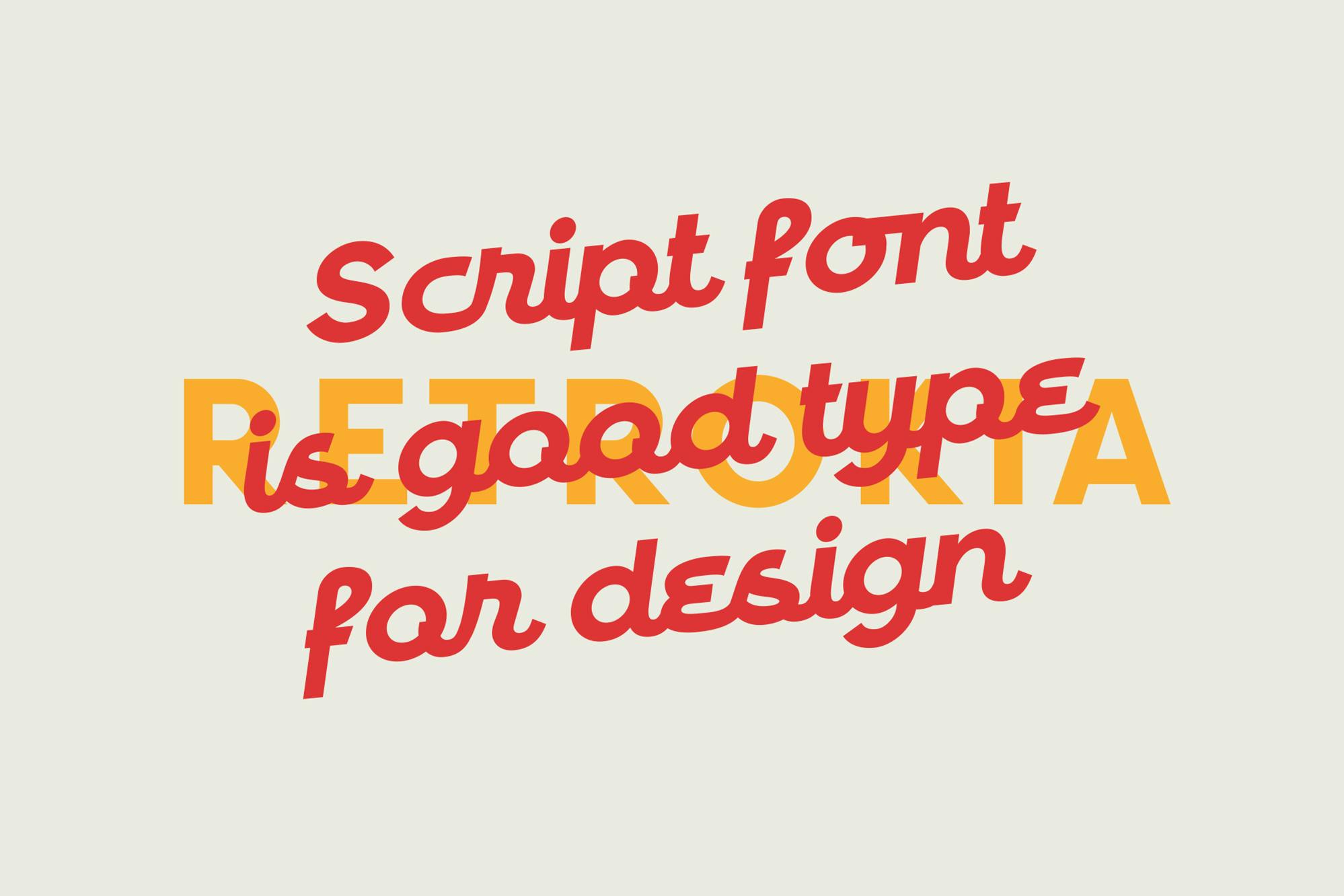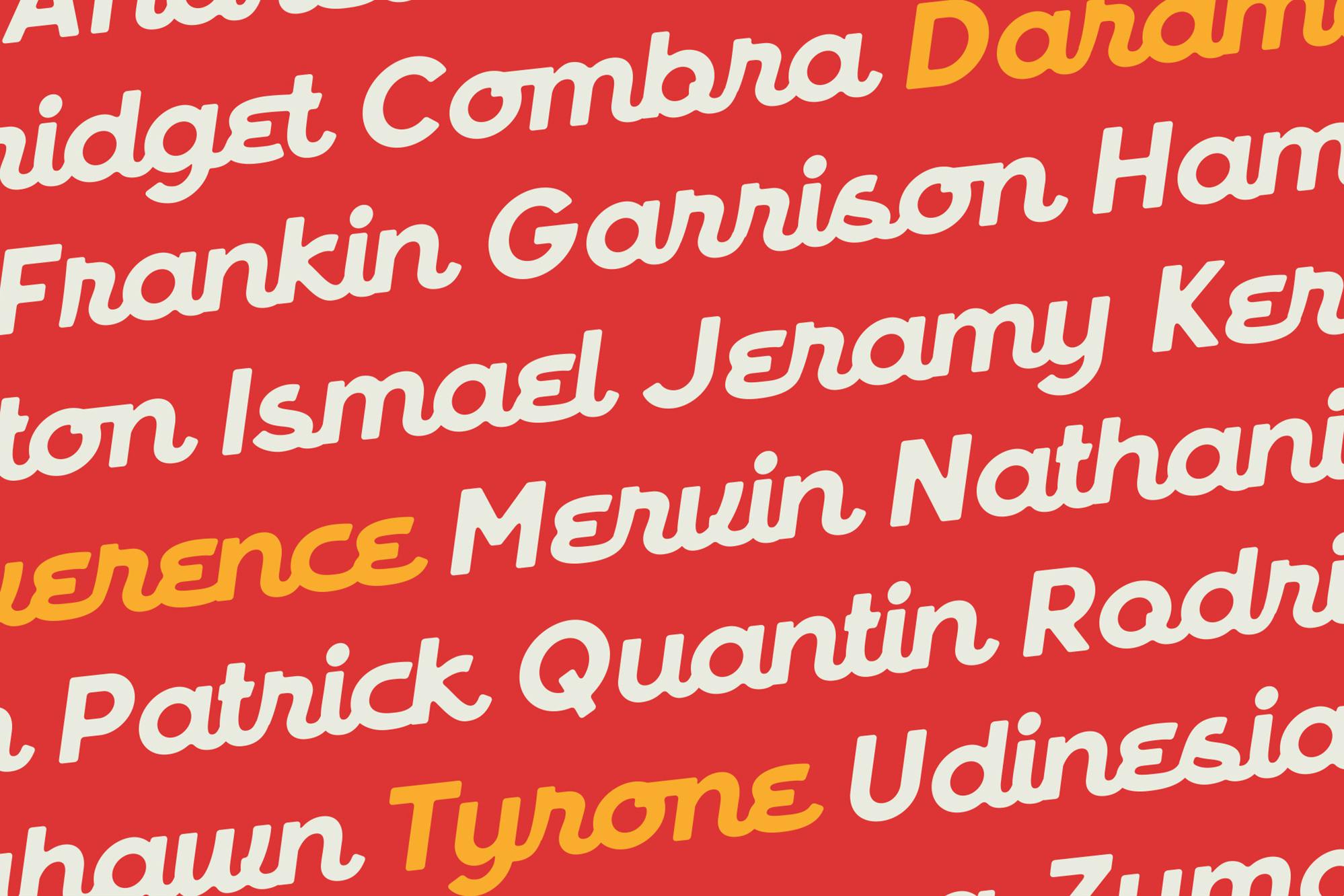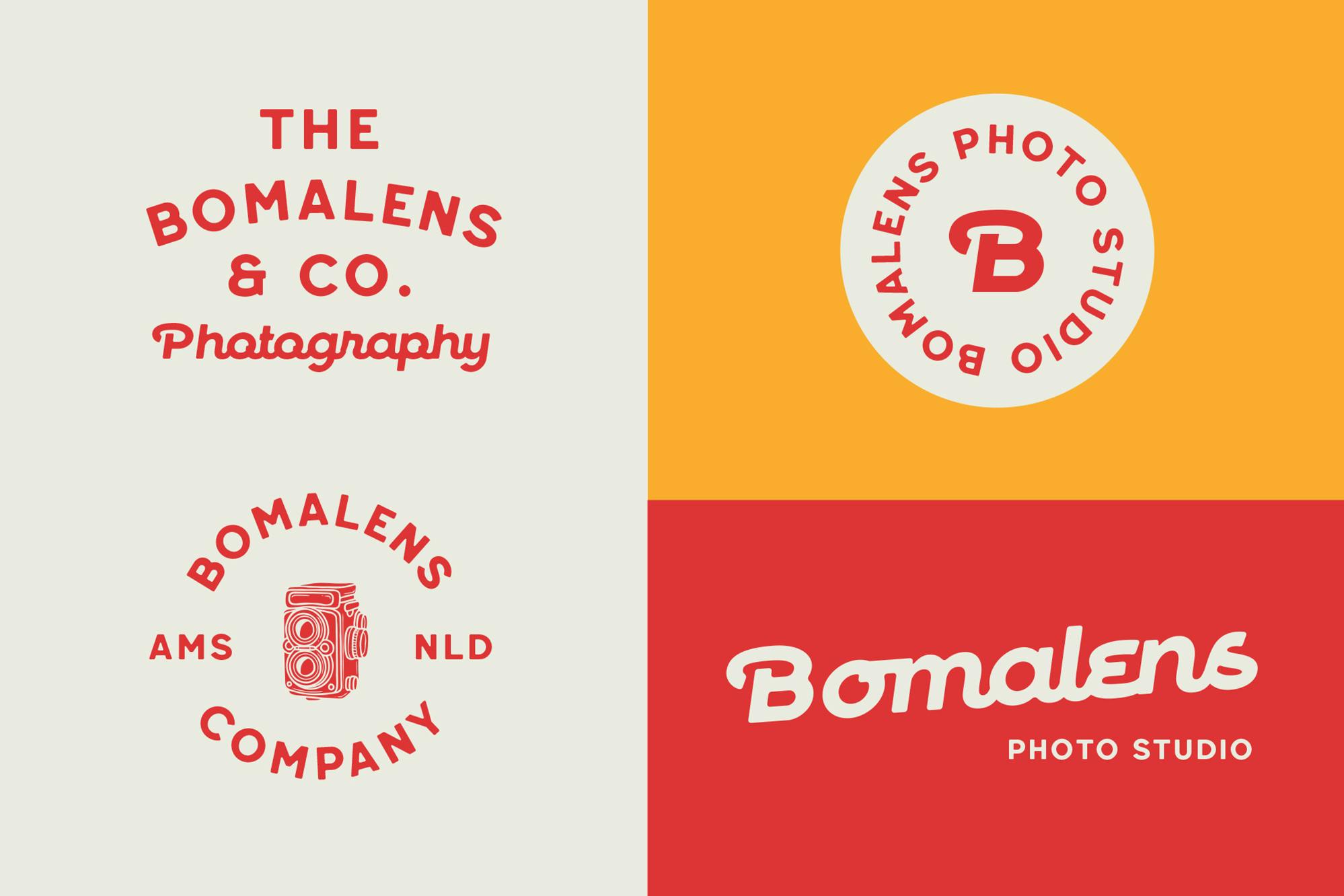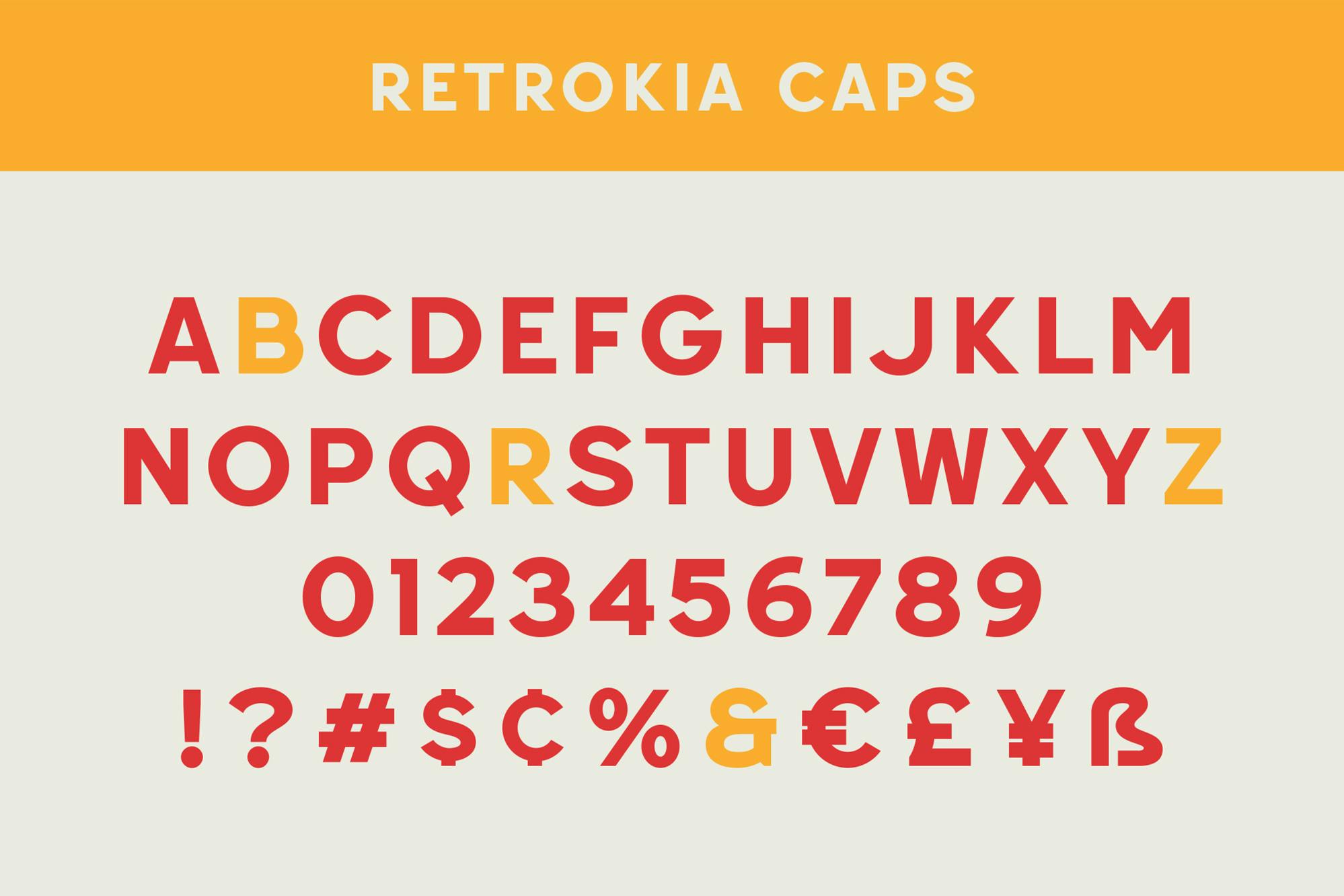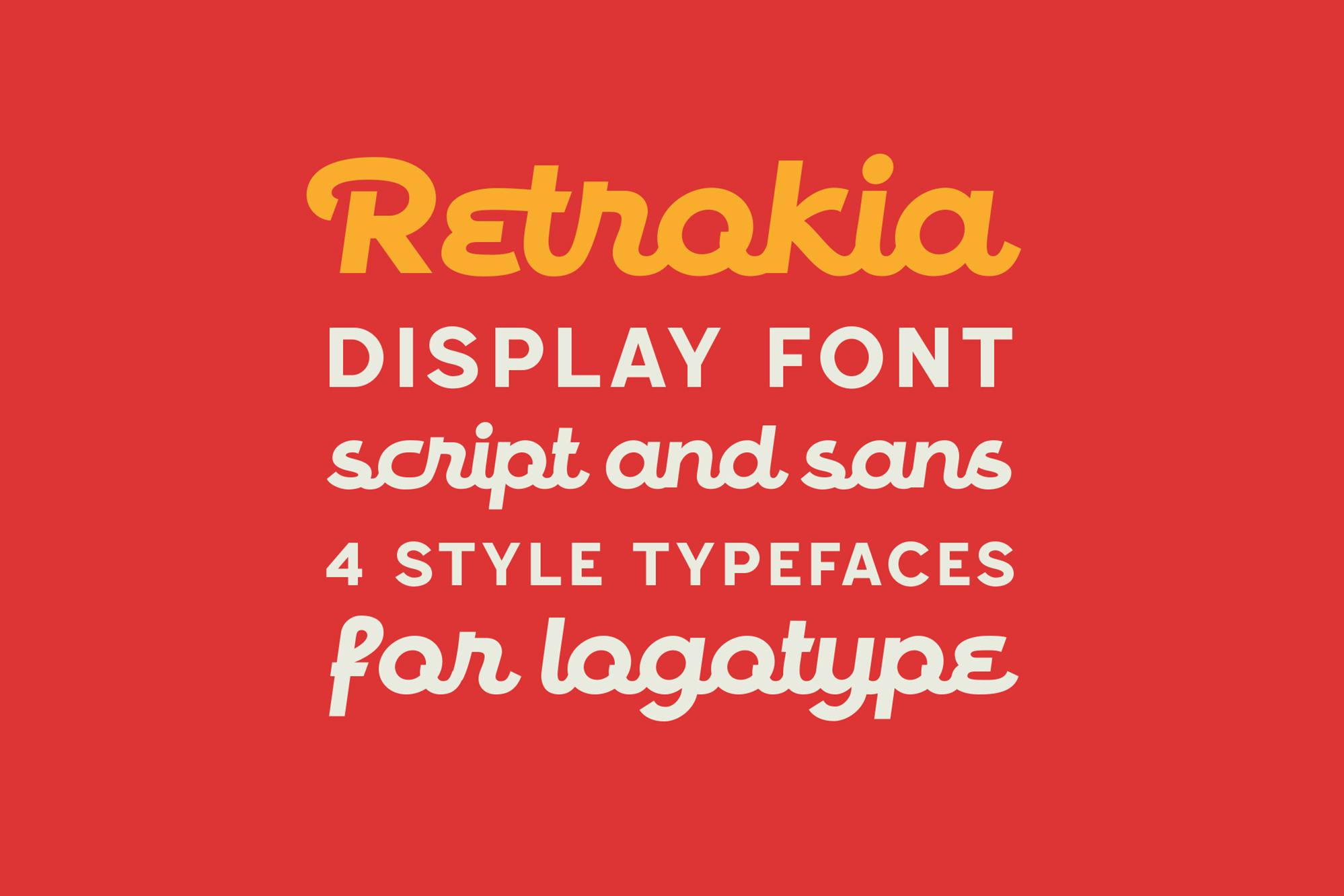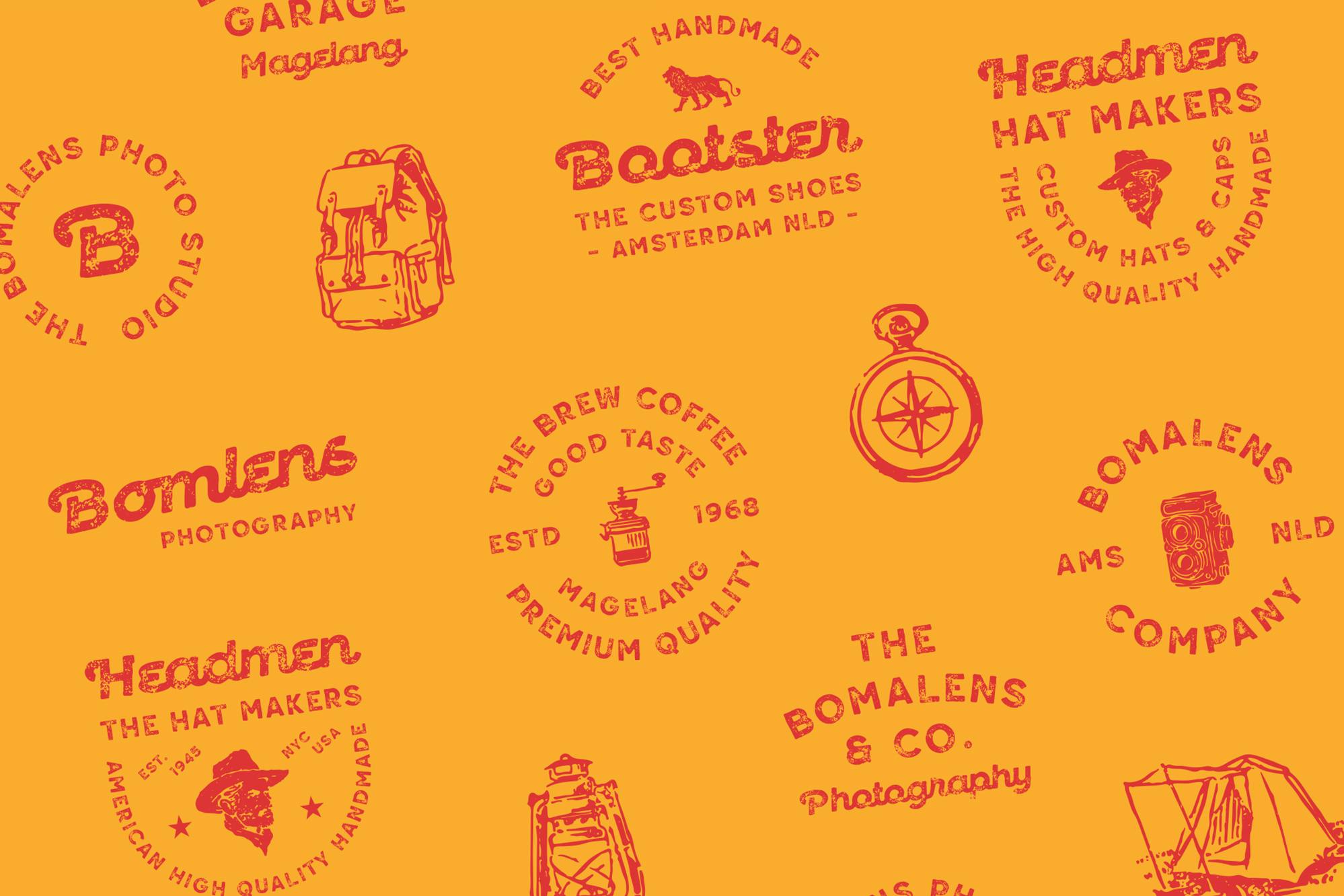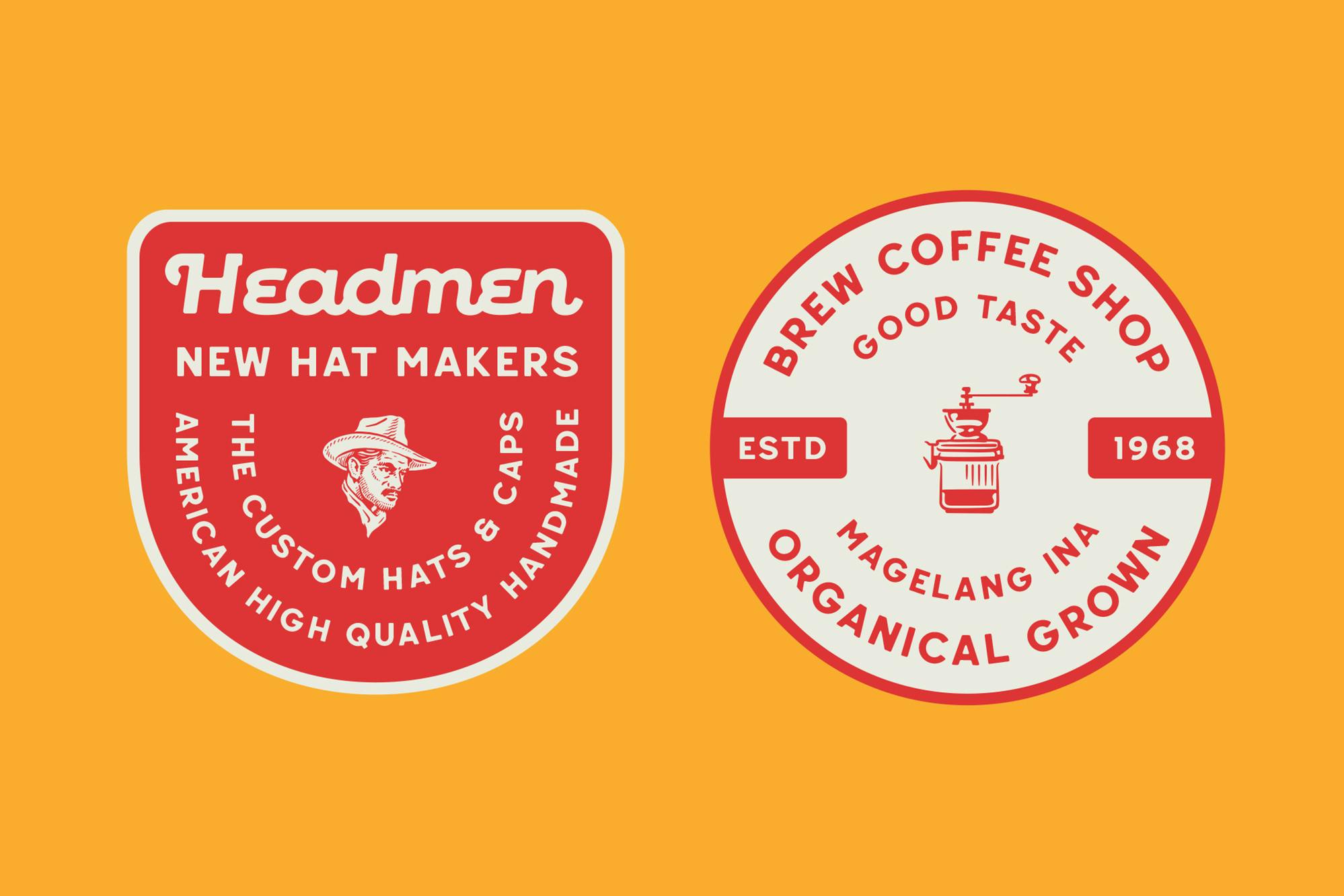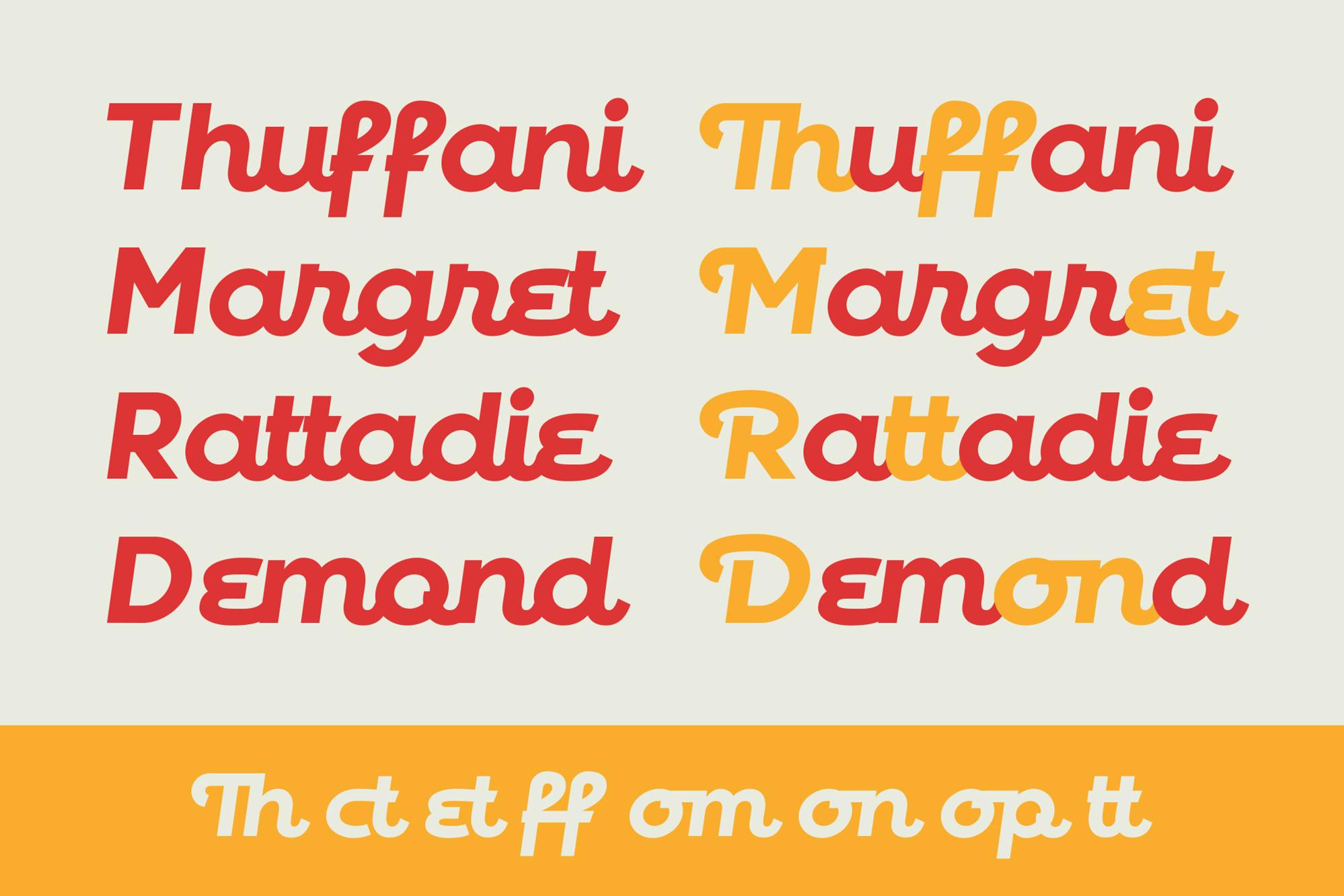
Retrokia Display Font
فونت رترکیای نمایش، بهترین انتخاب برای طراحی لوگو و بسته‌بندی.
کلکسیون فونت با نام "Retrokia"، یک فونت نمایش برای طراحی لوگو است. این مجموعه شامل فونت‌های اسکریپت و سن‌سریف می‌باشد. هر فونت با ۴ نوع استایل (معمولی، گرد، خشن و بافت‌دار) ارائه می‌شود. این فونت اسکریپت شامل برخی جایگزین‌ها و لیگاتورها است. فونت رترکیای نمایش در طراحی‌های مختلفی از جمله لوگو، پوستر، برچسب، نشان، بسته‌بندی، برندینگ، نقل‌قول‌ها و سایر طراحی‌های سفارشی کاربرد دارد.
ویژگی‌های فونت رترکیای:
• ۴ نوع استایل (معمولی، گرد، خشن و بافت‌دار)
• حروف بزرگ، کوچک، اعداد، نمادها، نشانه‌گذاری، جایگزین و لیگاتور در فونت اسکریپت
• حروف بزرگ، اعداد، نمادها و نشانه‌گذاری در فونت سن‌سریف
• چندزبانه